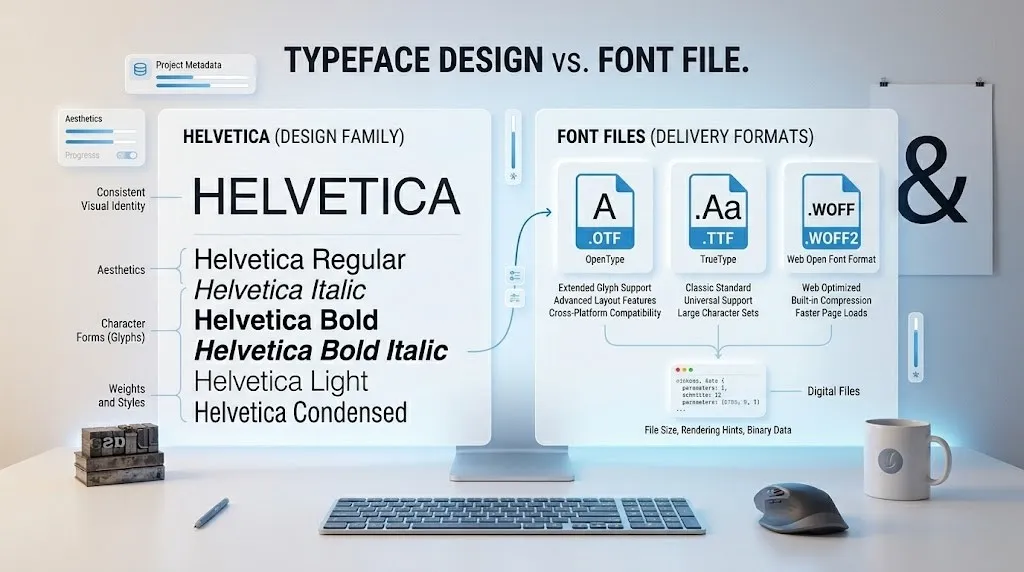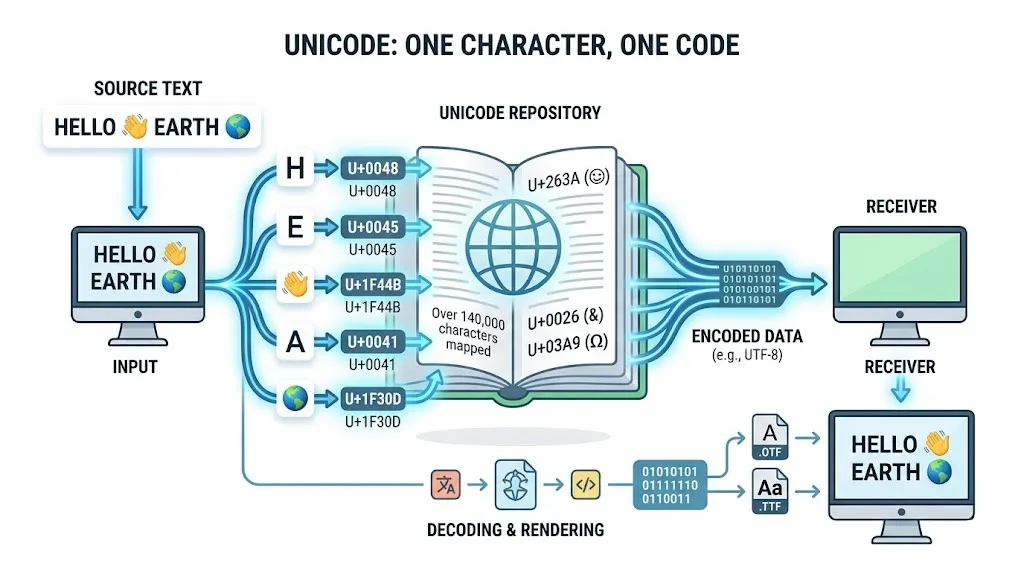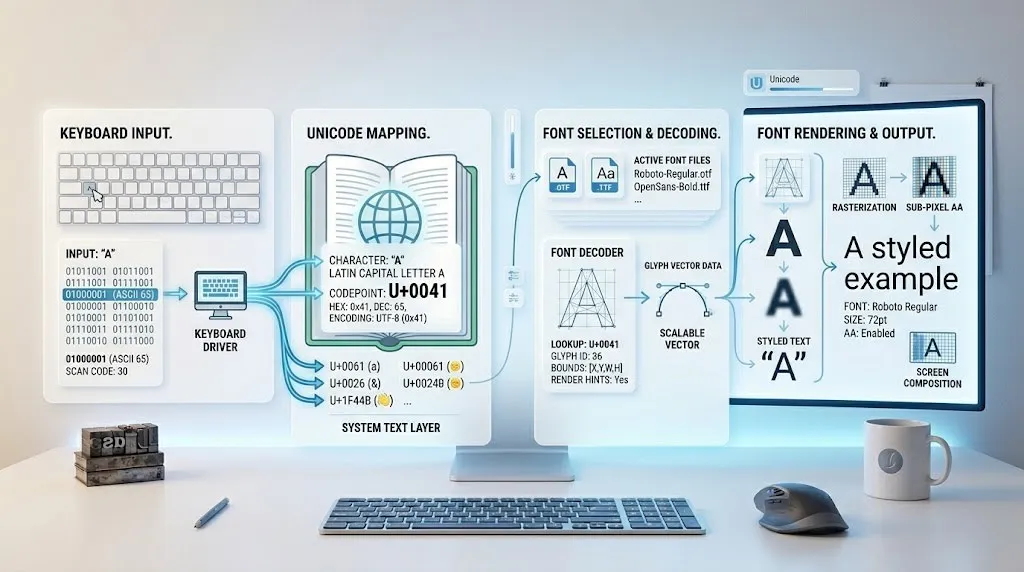
Unterschied zwischen Fonts, Schriftarten und Unicode – einfach erklärt
Kurze Antwort zuerst
Schriftart ist das visuelle Design von Buchstaben (z. B. wie „A“ aussieht). Font ist die digitale Datei, die dieses Design auf deinem Computer speichert. Unicode ist ein unsichtbarer weltweiter Standard, der jedem Zeichen eine eindeutige Nummer zuweist – unabhängig vom Aussehen. Kurz gesagt: Unicode sagt was ein Zeichen ist, die Schriftart sagt wie es aussieht, und der Font ist die Datei, die das umsetzt.
Warum verwechseln so viele Menschen diese drei Begriffe?
Wenn du auf deinem Computer einen Text tippst, passieren im Hintergrund mindestens drei verschiedene Dinge gleichzeitig. Dein Gerät speichert das Zeichen als Zahl, wählt ein Design für dieses Zeichen aus und zeichnet es dann auf den Bildschirm. Drei verschiedene Vorgänge – aber wir sehen nur das Ergebnis: einen Buchstaben.
Genau deshalb wirken Font, Schriftart und Unicode für die meisten Menschen wie dasselbe. Sie sind es aber nicht. Und wenn du einmal verstehst, wie die drei zusammenspielen, wird dir vieles klarer – warum manche Zeichen auf manchen Webseiten falsch dargestellt werden, warum eine Schriftart plötzlich „kaputt“ aussieht oder warum du auf Instagram keine echten Fettbuchstaben nutzen kannst.
Lass uns die drei Begriffe einzeln durchgehen – ohne komplizierte Fachsprache.
Unicode: die unsichtbare Grundlage hinter jedem Zeichen
Unicode die unsichtbare Grundlage hinter jedem Zeichen
Stell dir vor, du schickst jemandem in Japan einen Brief auf Deutsch. Der andere versteht kein Deutsch, und du verstehst kein Japanisch. Ihr braucht eine gemeinsame Sprache – eine Art Code, den beide Seiten kennen.
Genau das macht Unicode für Computer.
Computer können keine Buchstaben speichern. Sie kennen nur Zahlen. Unicode löst dieses Problem, indem es jedem Zeichen der Welt eine eindeutige Nummer gibt. Diese Nummern heißen Codepoints.
Das große „A“ hat zum Beispiel den Codepoint U+0041. Egal ob du auf einem Windows-PC, einem Mac, einem Android-Handy oder einem alten Linux-Server arbeitest – U+0041 bedeutet immer und überall das große lateinische „A“. Kein Durcheinander, keine Verwechslungen.
Dasselbe gilt für Emojis. Das Emoji 😀 hat den Codepoint U+1F600. Wenn du dieses Emoji an jemanden schickst, schickt dein Gerät eigentlich nur diese Zahl. Das Empfangsgerät schaut dann in seiner eigenen Font-Datei nach, wie es diesen Code zeichnen soll – deshalb sehen Emojis auf Apple-Geräten etwas anders aus als auf Samsung-Handys, obwohl es dieselbe Zahl dahinter gibt.
Unicode kümmert sich also nur um die Bedeutung eines Zeichens, nicht um sein Aussehen.
Wie groß ist Unicode eigentlich?
Unicode ist riesig. Der Standard enthält – ich empfehle dir, die genaue aktuelle Zahl auf der offiziellen Seite unicode.org zu prüfen, da dieser Wert mit jeder neuen Version wächst – weit über 100.000 Zeichen. Dazu gehören lateinische Buchstaben, kyrillische Schrift, arabische Zeichen, chinesische Schriftzeichen, Hieroglyphen, mathematische Symbole, Musiknoten und natürlich Emojis.
Nicht jede Font-Datei unterstützt alle davon. Das ist einer der wichtigsten Punkte, der später noch eine Rolle spielt.
Schriftart: das Design hinter den Zeichen
Wenn Unicode die Bedeutung festlegt, dann legt die Schriftart das Aussehen fest.
Eine Schriftart (auf Englisch typeface) ist die künstlerische Gestaltung von Zeichen. Sie bestimmt, ob ein „A“ mit oder ohne kleine Querstriche (sogenannte Serifen) gezeichnet wird, ob die Linien dünn und elegant oder breit und kräftig sind, ob der Text verspielt oder sachlich wirkt.
Hier einige Beispiele, die du wahrscheinlich kennst:
• Helvetica – klar, modern, sachlich, überall in der Werbung und auf Hinweisschildern
• Times New Roman – klassisch, mit Serifen, lange Zeit Standard in Zeitungen und Büchern
• Comic Sans – locker, rund, viel gehasst, aber für manche Leser mit Lesestörungen tatsächlich hilfreich
• Georgia – eine Webschriftart mit Serifen, gut lesbar auf Bildschirmen
Eine Schriftart ist kein einzelnes Ding, sondern eher eine Familie. Helvetica zum Beispiel gibt es in vielen Varianten: Helvetica Regular, Helvetica Bold, Helvetica Italic, Helvetica Light und so weiter. Diese Varianten nennt man Schnitte.
Die Schriftart legt also das Gesamtdesign fest. Der einzelne Schnitt (fett, kursiv, schmal) ist dann eine bestimmte Ausprägung davon.
Schriftart vs. Zeichensatz – ein kleiner Unterschied, der oft vergessen wird
Manchmal hörst du auch den Begriff Zeichensatz. Das ist nicht dasselbe wie eine Schriftart.
Ein Zeichensatz ist eine Liste von Zeichen – zum Beispiel alle Buchstaben des lateinischen Alphabets plus Zahlen plus gängige Sonderzeichen. Er sagt aber nicht, wie diese Zeichen aussehen. Ein Zeichensatz ist wie ein Inhaltsverzeichnis ohne die eigentlichen Seiten.
FontEine digitale Datei (.ttf, .otf, .woff)Speichert das Design und setzt es auf dem Bildschirm um
Die drei arbeiten immer zusammen: Unicode sagt was, die Schriftart sagt wie es aussehen soll, und der Font sagt dem Bildschirm wie es gezeichnet wird.
Wenn du das nächste Mal auf deiner Webseite eine neue Schriftart einbindest oder in einem Designprogramm eine Schriftart auswählst, weißt du jetzt, was im Hintergrund passiert. Das macht die ganze Typografie-Welt ein gutes Stück weniger mysteriös.